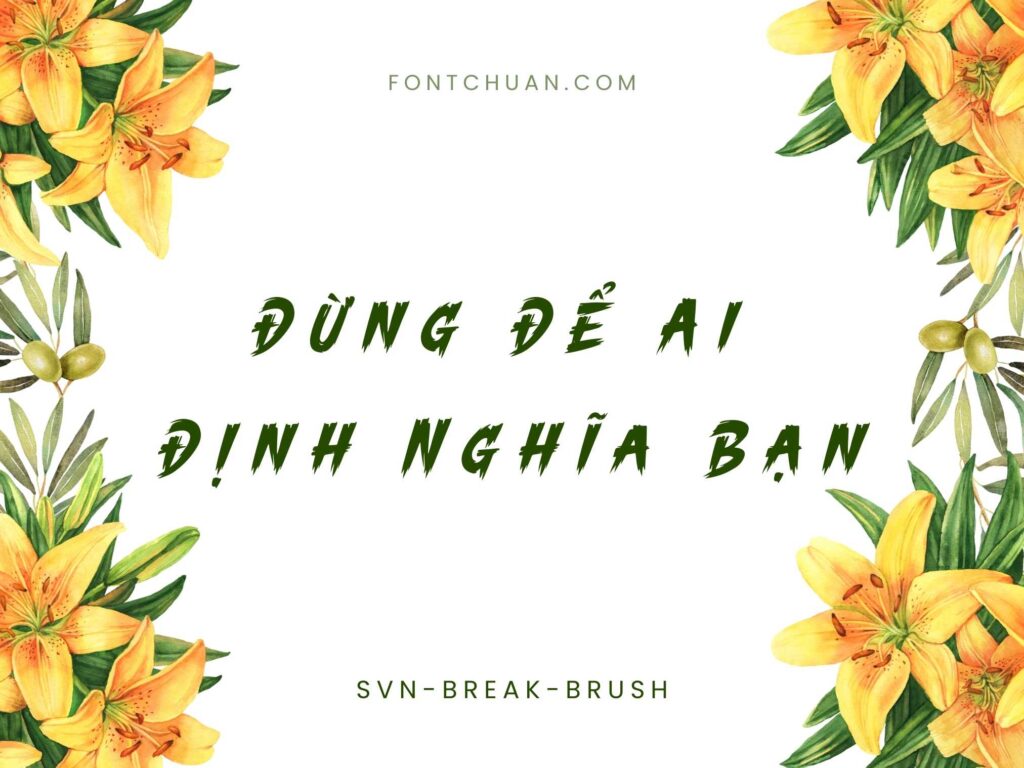
Font SVN Break Brush Việt Hóa
Tác giả Font: Bangkit Tri Setiadi
Break Brush là một font chữ được thiết kế bởi Blankids Studio, lấy cảm hứng từ nghệ thuật viết chữ bằng cọ trong typography. Font này mang phong cách vui tươi và thu hút, lý tưởng cho các thiết kế cần sự nổi bật. Font đã được Việt hóa để hỗ trợ tiếng Việt bởi Styleno.1 Fonts, đồng thời hỗ trợ nhiều ngôn ngữ khác, giúp mở rộng phạm vi sử dụng trên toàn cầu. Font này được thành viên của Font Chuẩn sưu tầm và chia sẻ, đáp ứng nhu cầu của bạn đọc và ứng dụng thực tế vào các dự án thiết kế.
Đặc điểm thiết kế của Break Brush bao gồm các đường nét mạnh mẽ và tự nhiên, tạo cảm giác như chữ viết tay bằng cọ thực sự. Font này phù hợp cho các ứng dụng như thiết kế logo, tiêu đề, nhãn mác và các dự án sáng tạo khác. Các ngành nghề phù hợp bao gồm quảng cáo, nghệ thuật và thiết kế đồ họa.